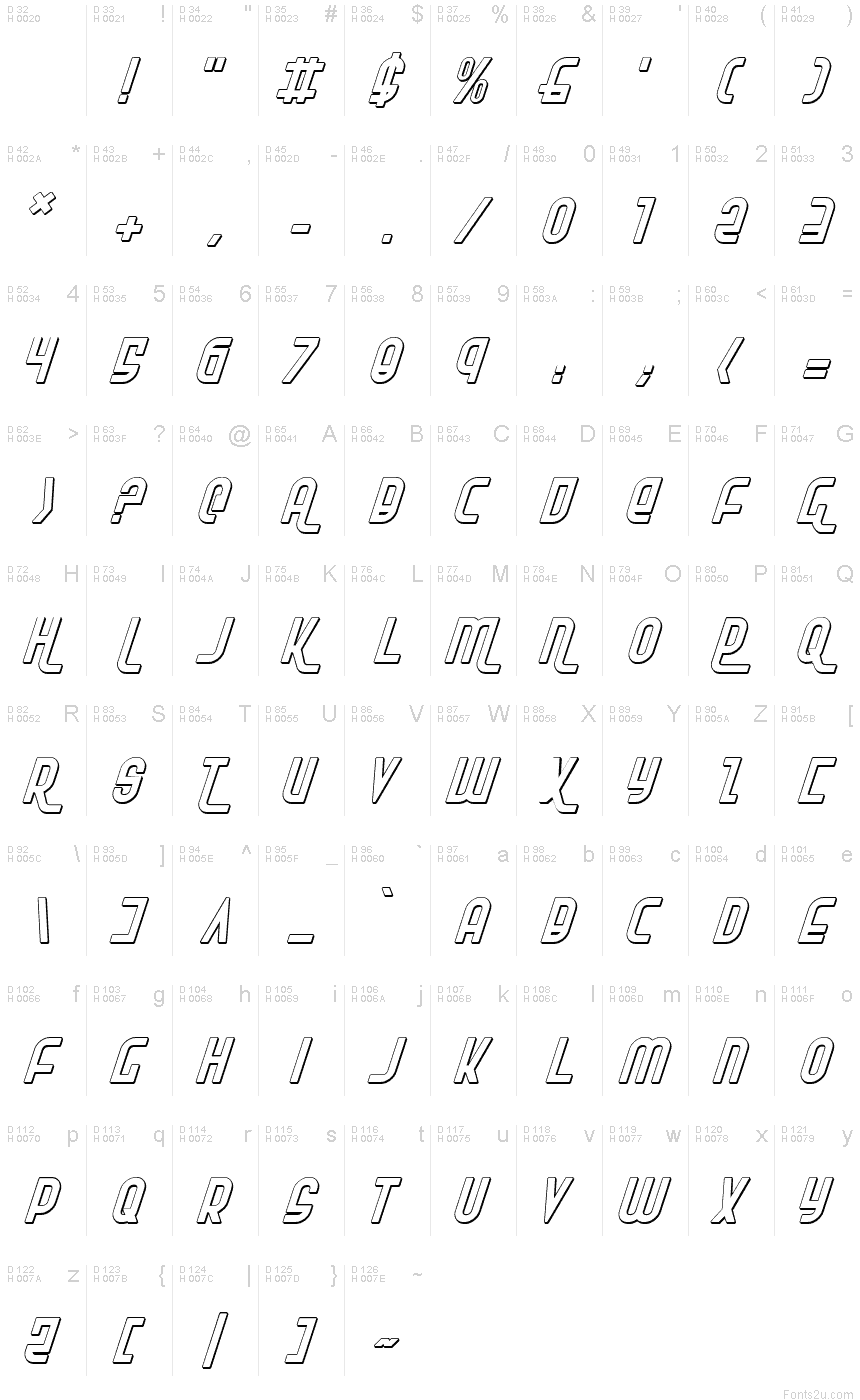
Ro'Ki'Kier Shadow Italic od Iconian Fonts to darmowy, retro font typu display z obrysowanymi znakami i ukośnym charakterem, przywodzącym na myśl starą fantastykę naukową oraz liternictwo customowych aut. Wielkie litery są szerokie, dynamiczne i sprawiają wrażenie elastycznych. Dzięki grubym konturom i schodkowemu cieniowi napisy zyskują wyrazisty, plakatowy wygląd, wykraczający poza zwykły efekt obrysu.
Ten darmowy krój najlepiej sprawdza się tam, gdzie potrzebujesz wyrazistego klimatu z epoki – logotypy w stylu arcade, okładki komiksów, plansze tytułowe, ulotki zespołów czy grafiki na gadżety. Ponieważ cień jest wbudowany w litery, font świetnie radzi sobie w krótkich nagłówkach i inicjałach, gdzie ta wrodzona głębia wykonuje za Ciebie całą robotę.
Ro'Ki'Kier Shadow Italic